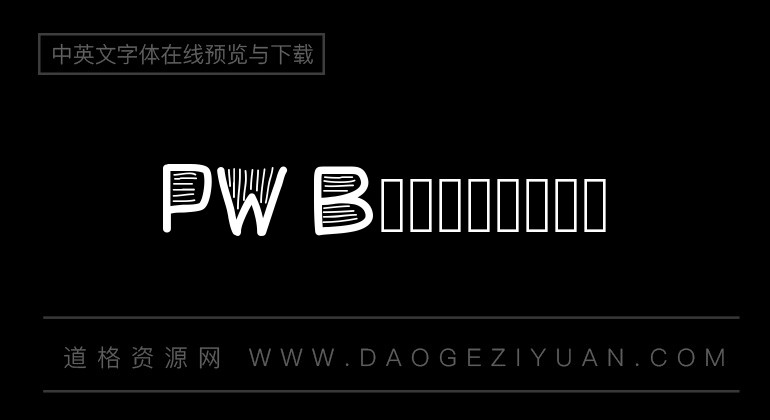
PW Beardfont
? PW Beardfont是一款由PW Graphics公司设计的自由字体,它具有清晰、粗犷的外观,能够更好地表达您的想法。它具有独特的设计,可以用于任何类型的设计,包括海报、报纸、网页、广告和印刷品。PW Beardfont字体可以帮助您让您的作品更加突出,从而更好地吸引观众。
PW Beardfont是一款非常不错的手写艺术字体,具有很好的视觉感,适合于文化类的宣传设计、商业类品牌的广告和产品包装设计以及个性化文字排版等较多场景。
PW Beardfont字符映射图